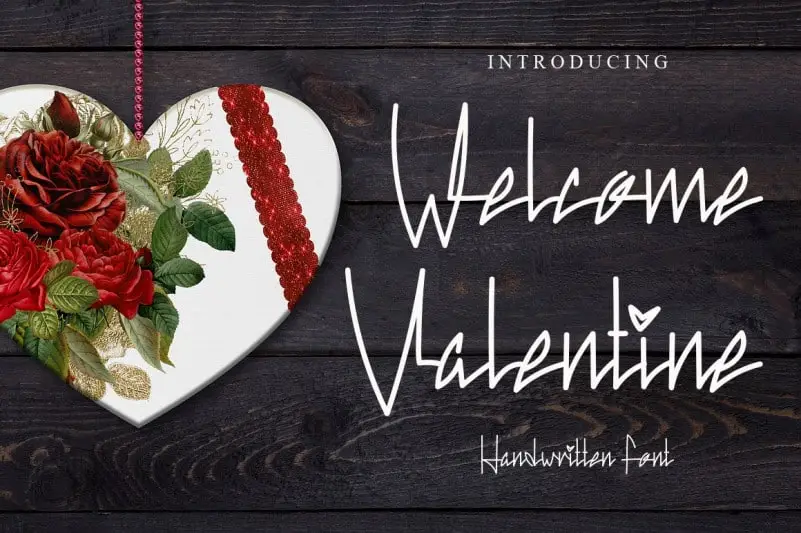
Welcome Valentine Script Font – Download Grátis
A Welcome Valentine Script Font é uma fonte escrita à mão única, que possui aspectos desequilibrados e intrigantes. Este tipo especializado traz aos designers e criadores de conteúdo a oportunidade de adicionar um toque singular e interessante a seus projetos. Não importa qual seja o tema ou o projeto específico em que você esteja trabalhando, esta fonte será uma valiosa adição ao seu acervo de fonts. Ela tem potencial para dar uma elevada qualidade à qualquer criação, tornando-a ainda mais única e atrativa. Inspirada no estilo do amor romântico do Dia dos Namorados, Welcome Valentine Script Font é perfeita para aqueles que desejam imprimir personalidade em seus projetos de escrita digital. Com essa fonte adicional a sua disposição, você terá o poder de criar mensagens e designs cheias de vida e emoção.